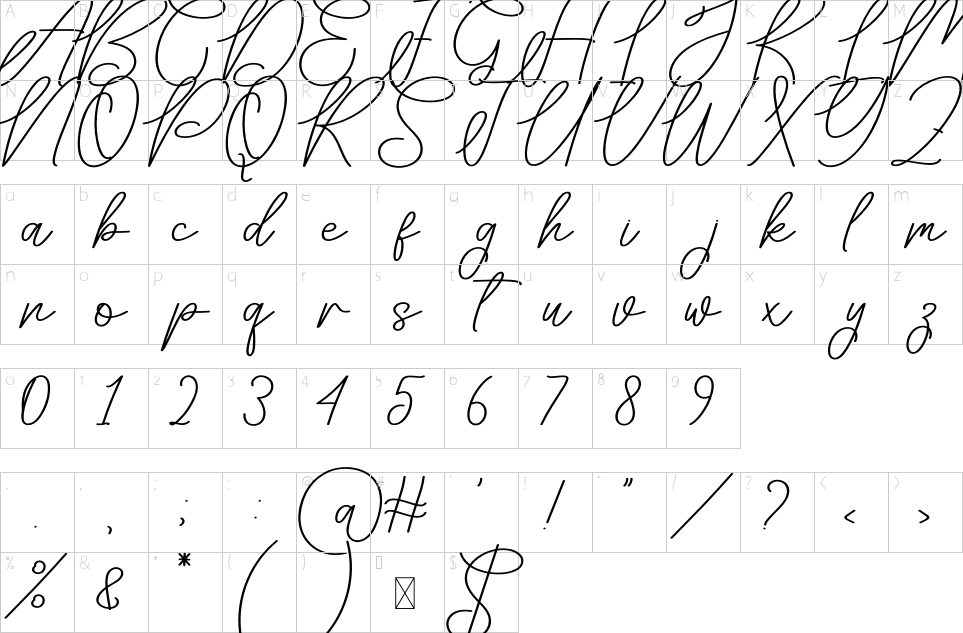
Descubra a nova fonte já esperada, ‘Already Font’, disponível gratuitamente para download para Windows e Mac. Desenvolvida por scratchones, esta elegante fonte já foi baixada 359 vezes. Seja para assinar nomes, separar listas ou criar títulos chamativos, ‘Already Font’ adiciona um toque de sofisticação a qualquer projeto. Seja você um profissional de design ou um iniciante, esta fonte cheia de opções de tamanho e estilo é uma escolha perfeita para tornar seus projetos ainda mais expressivos. Não perca esta oportunidade de adicionar uma fonte de qualidade gratuita à sua coleção de recursos gráficos.